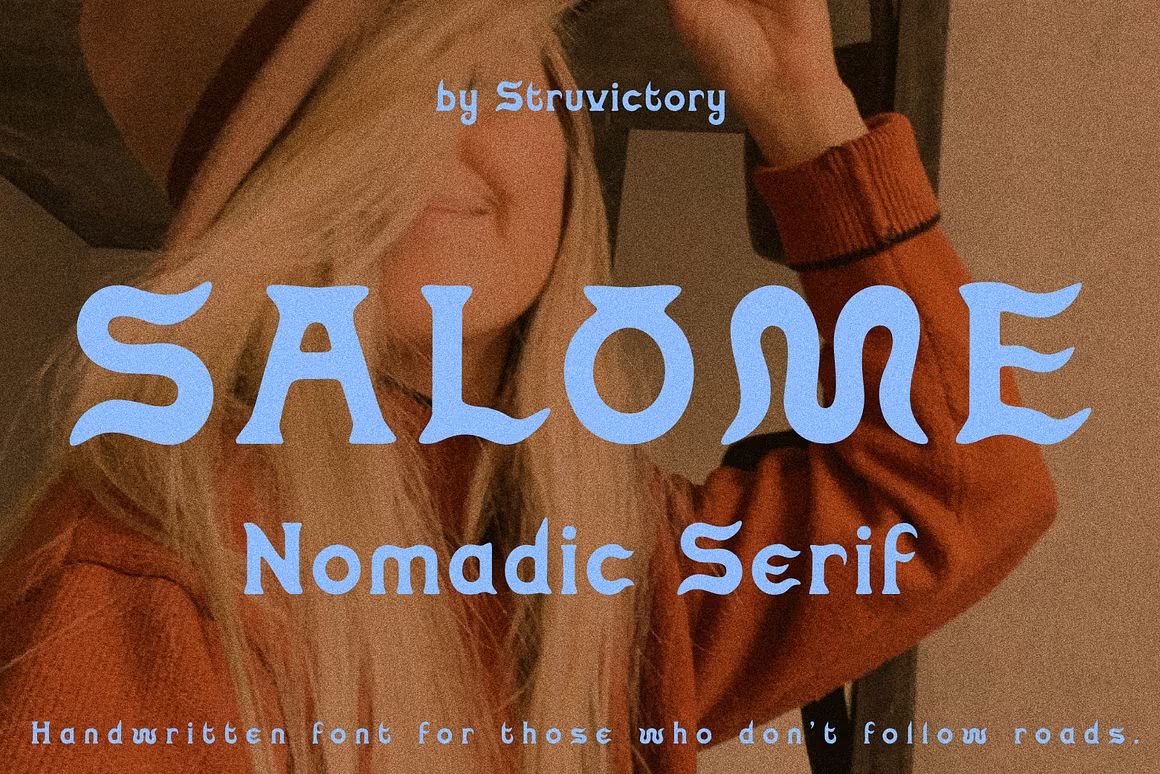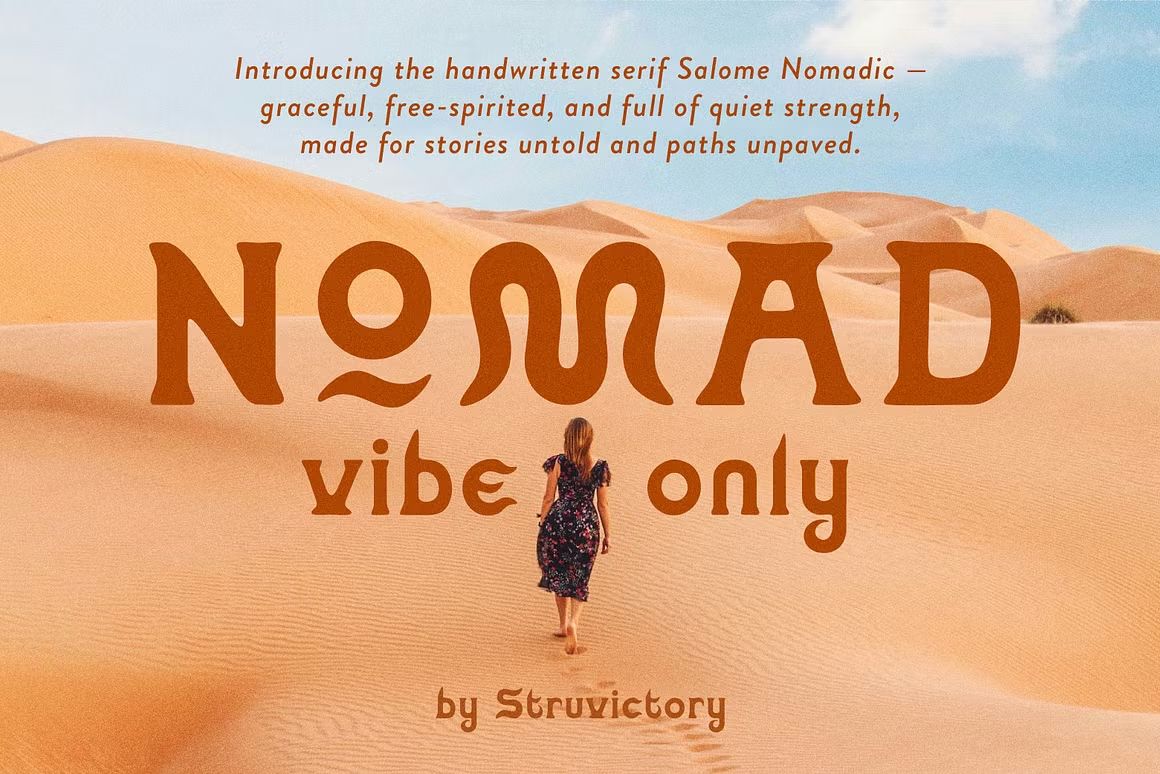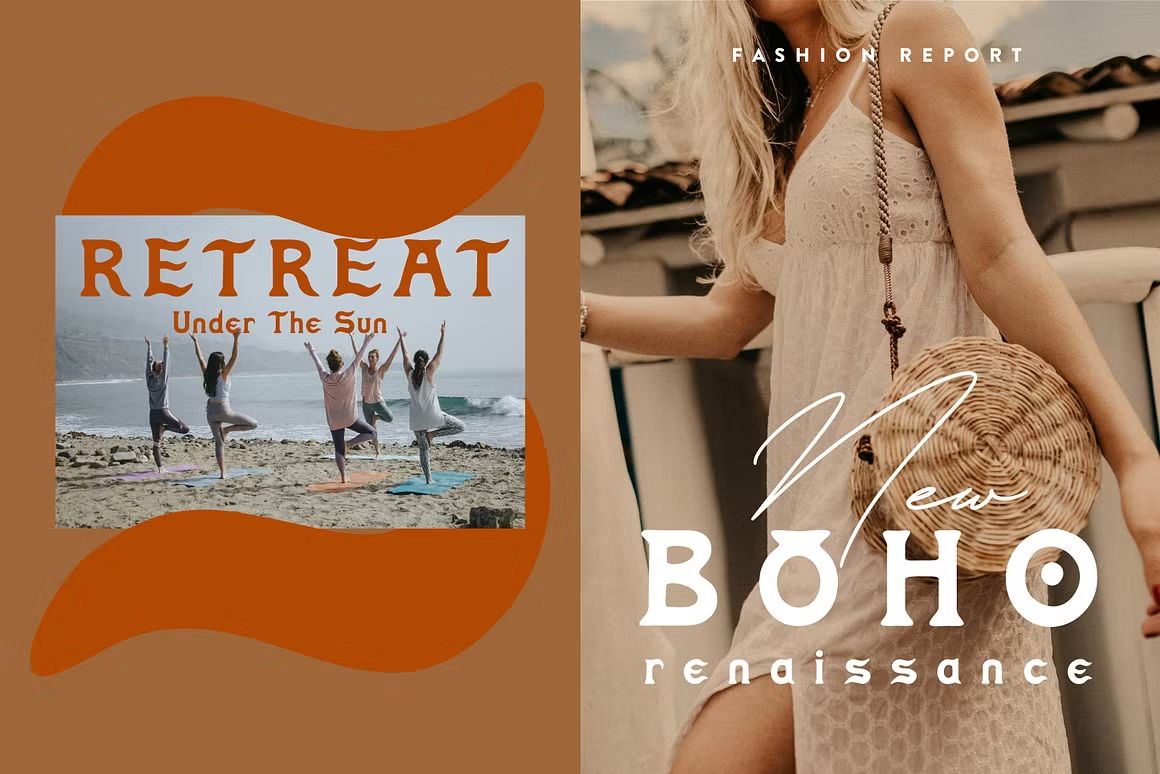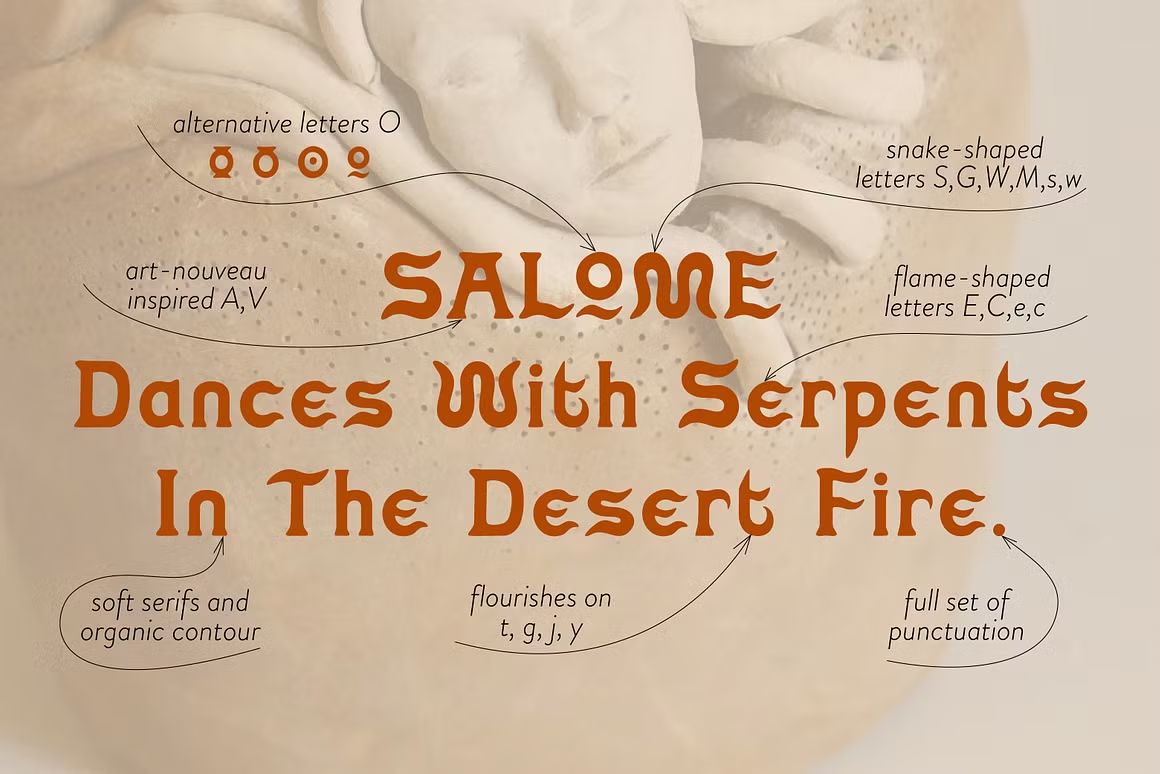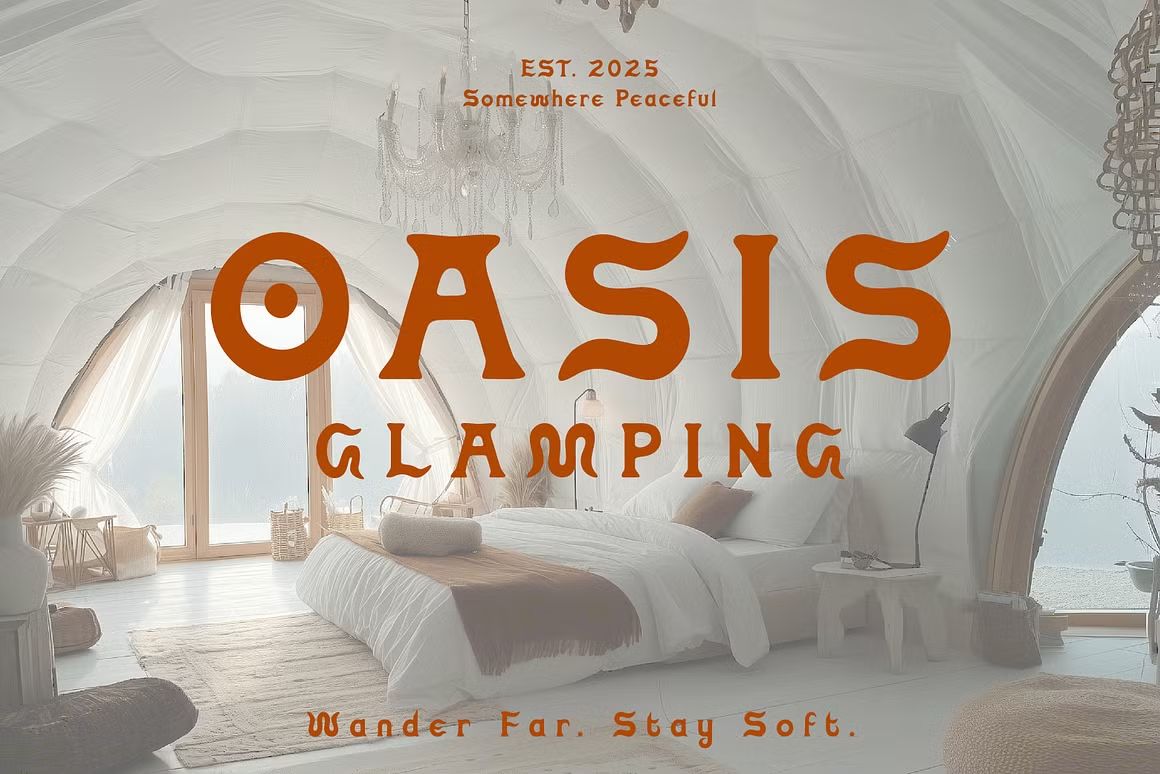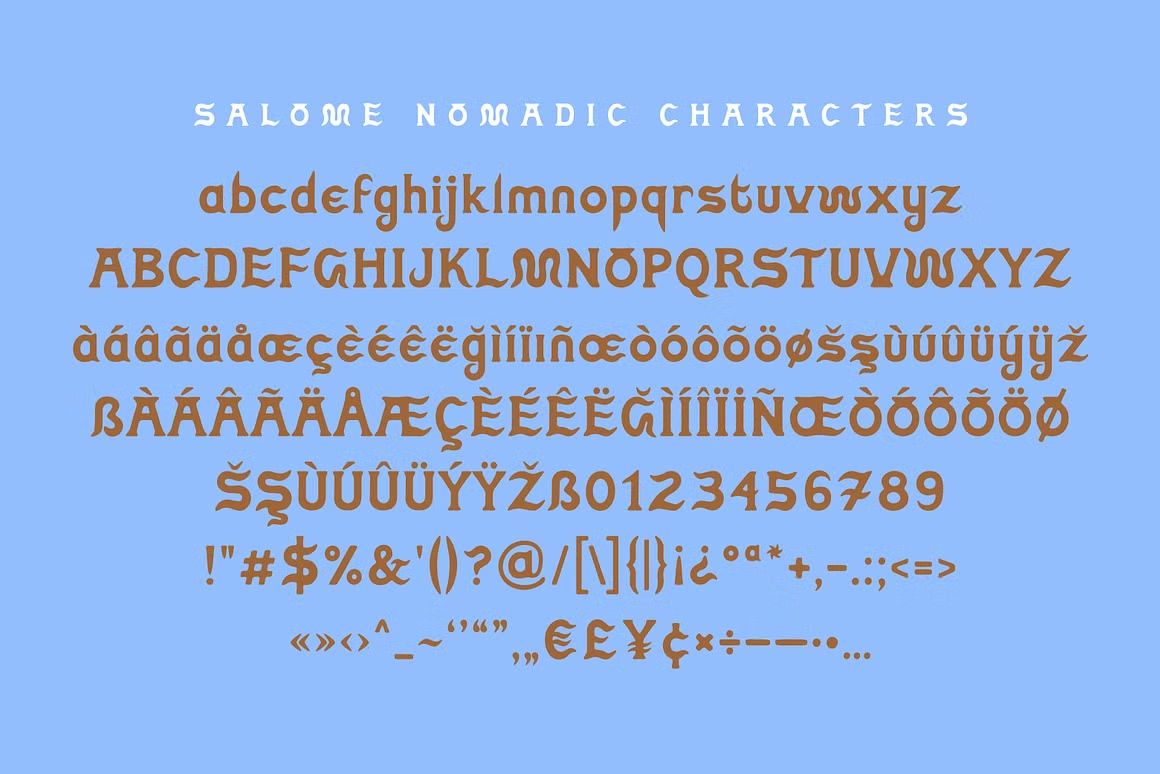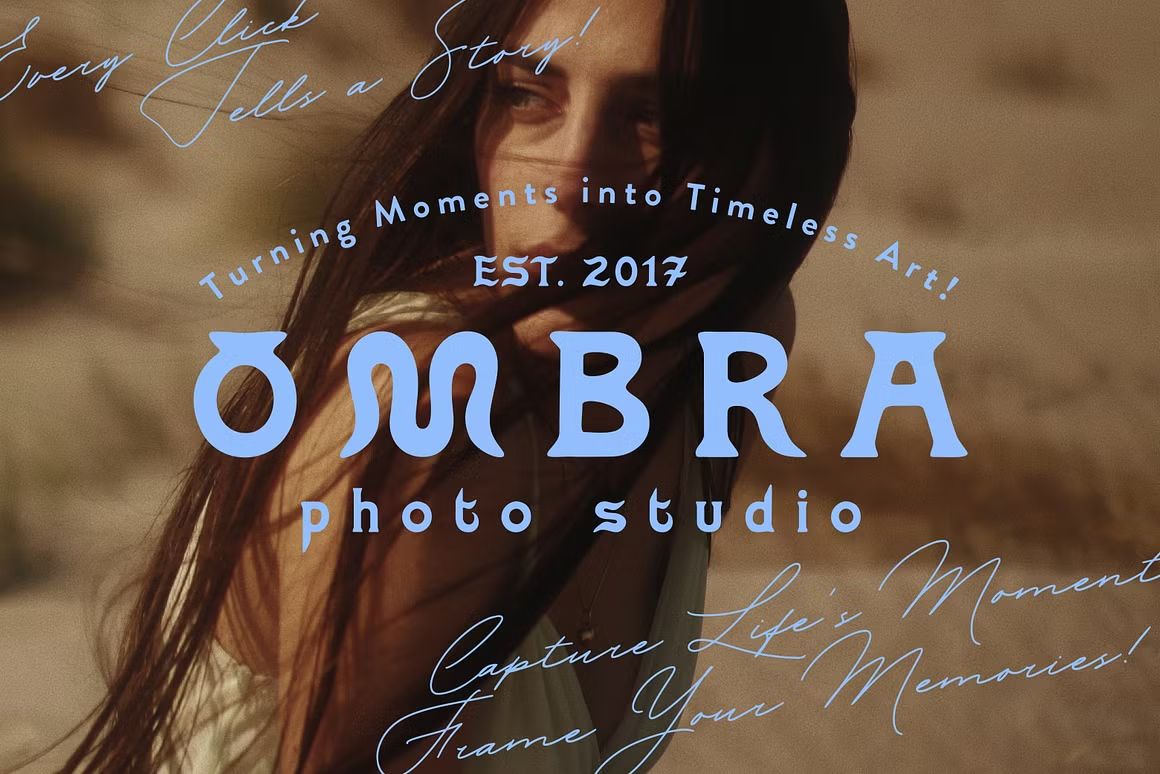
Salome Nomadic – Serif Font
Salome Nomadic adalah font serif elegan dengan sentuhan editorial dan modern. Cocok untuk branding, editorial, dan desain premium. Format OTF/TTF/WOFF, siap digunakan.
Salome Nomadic adalah font serif bergaya editorial dengan karakter elegan dan detail halus. Didesain dengan perpaduan klasik dan modern, font ini sangat cocok untuk editorial design, branding premium, majalah, judul mode, serta proyek kreatif yang membutuhkan sentuhan sophisticated. Bentuk hurufnya yang unik memberikan kesan artistik dan high-end dalam setiap aplikasi visual.
• Serif elegan dengan gaya editorial modern
• Ideal untuk branding mewah, editorial, dan desain fashion
• Termasuk huruf besar, kecil, angka, simbol, dan ligatur